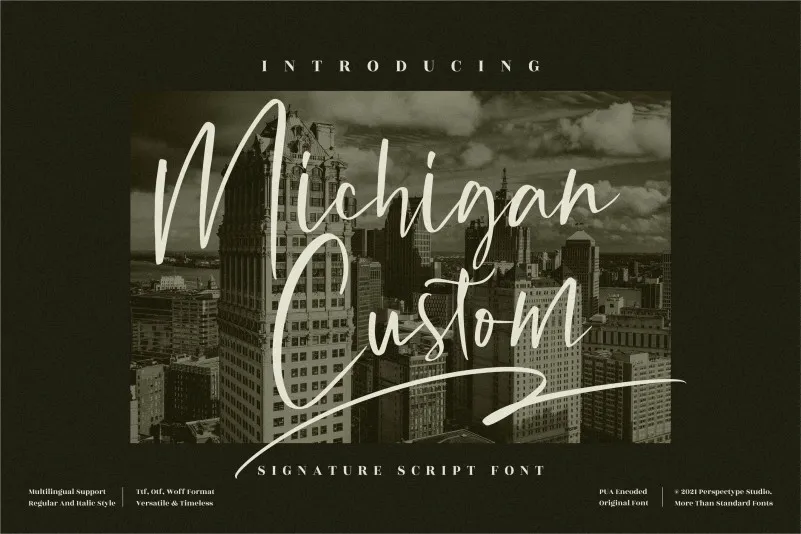
Michigan Custom Font
Esta é uma fonte script fina e elegante que se destaca por seu estilo moderno e sofisticado. Ela é ideal para adicionar um toque autêntico a uma variedade de projetos gráficos, desde convites de casamento até cartões de agradecimento, cartazes com citações ou cartas de presentes. Suas linhas finas criam um efeito encantador que traz vida e personalidade para qualquer projeto onde ela é aplicada — seja em cartões de aniversário, selos corporativos ou até mesmo logos. A Michigan Custom Font não só se torna uma escolha perfeita para quem busca um elemento hand-written moderno, mas também oferece o conforto de uma fonte cuidadosamente projetada com muitas opções de personalização. Com esse design único, você pode criar experiências gráficas que deixam seu projeto ainda mais impactante e atraente. A Michigan Custom Font é perfeita para designers em busca de algo diferente e sofisticado. Suas linhas leves, combinadas com um estilo moderno, permitem personalização e adaptação a diversas necessidades de design. Este é um recurso gráfico que não só oferece valor por sua elegância singular, mas também pela variedade de possibilidades criativas que ele proporciona. É uma escolha definitiva para quem busca dar um toque autêntico e único a seus projetos mais importantes, seja em cartões de agradecimento, selos corporativos ou até mesmo em elementos de marca.